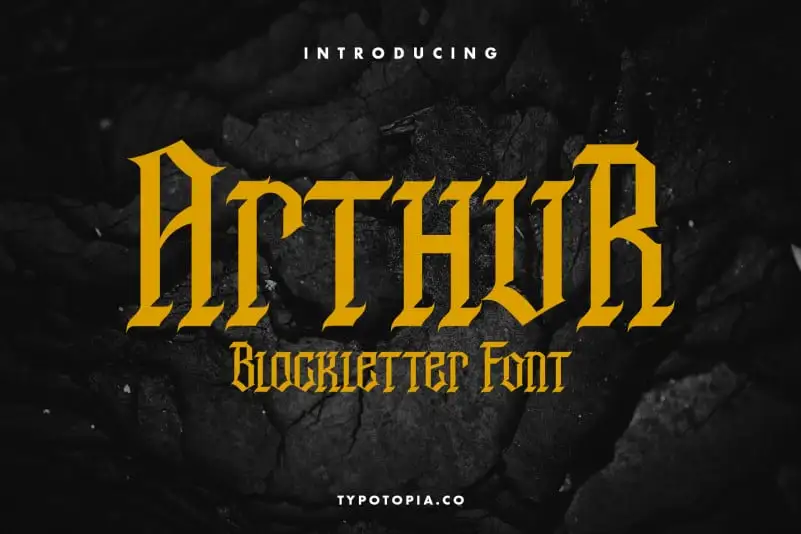
Arthur Blackletter Font – Fonte Grátis
Arthur Blackletter Font
Descubra a essência única do Arthur Blackletter Font em sua próxima peça de design. Este exclusivo tipo de letra blackletter foi criado para dar vida à sua arte e deixar uma impressão duradoura. Com seu estilo elegante e arquetípico, Arthur Blackletter é perfeito para revistas históricas, frontispícios bíblicos ou qualquer projeto que busque um toque distintivo de época. Seja você um designer gráfico experiente ou iniciante, achará-lo fácil de usar e versátil. Experimente sua elegância hoje, em seu design!